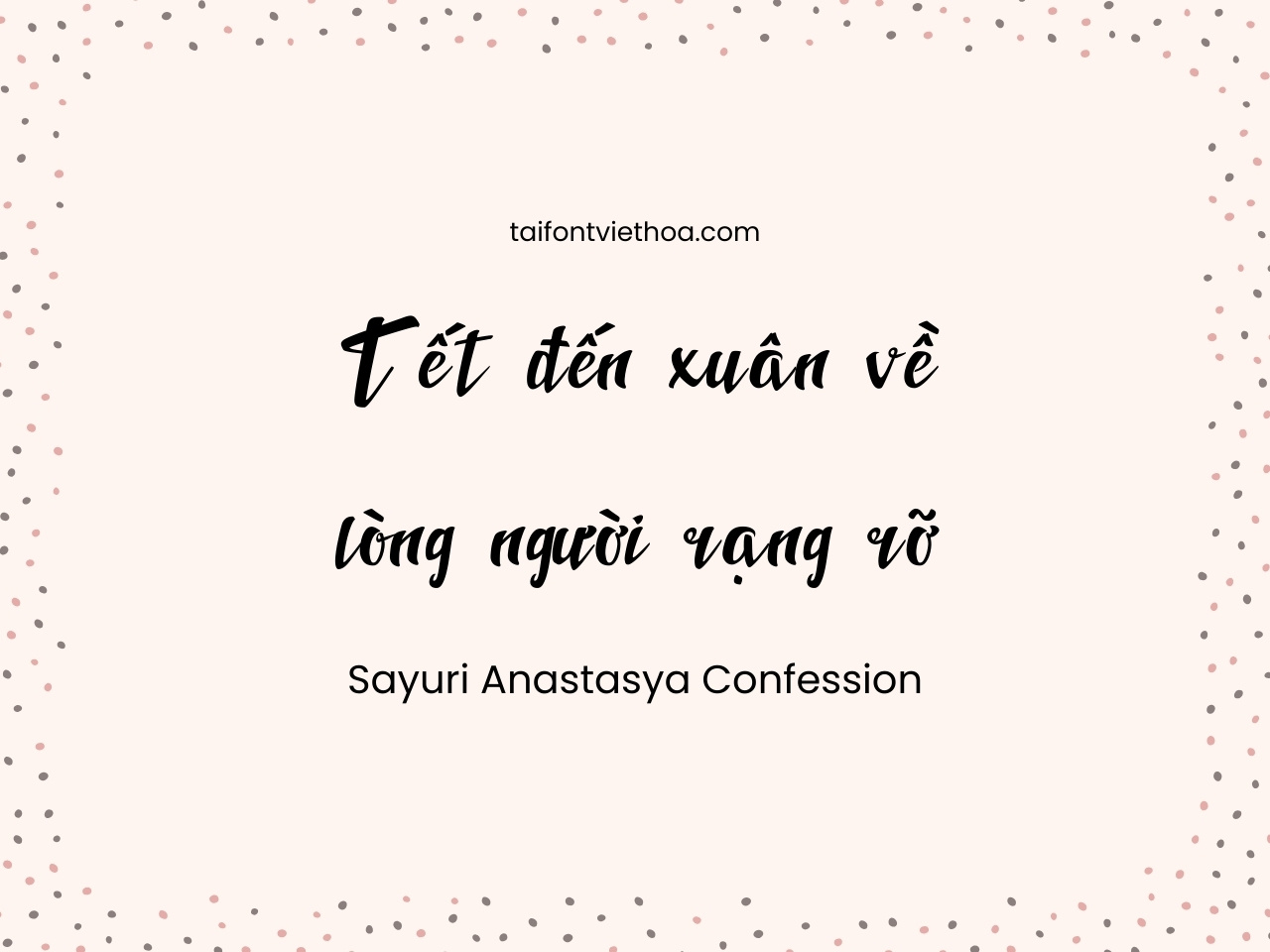
Font việt hóa Sayuri Anastasya Confession
Giới thiệu về font Sayuri Anastasya Confession
Sayuri Anastasya Confession là một font chữ script mang phong cách lãng mạn và đầy cảm xúc, thường được sử dụng trong các thiết kế nữ tính, thiệp cưới và branding nhẹ nhàng. Font được Việt hóa bởi Sayuri, hỗ trợ đầy đủ tiếng Việt với hệ dấu mềm mại, rõ ràng và sắc nét. Ngoài tiếng Việt, font còn tương thích với hơn 40 ngôn ngữ nhờ tích hợp bảng mã Latin và Latin Extended, giúp nhà thiết kế dễ dàng triển khai các dự án đa quốc gia. Font đã được taifontviethoa.com chọn lọc và kiểm duyệt chất lượng thực tế, sẵn sàng phục vụ cộng đồng sáng tạo Việt Nam trong nhiều ứng dụng thiết kế mang tính cảm xúc và thẩm mỹ cao.
Đặc điểm thiết kế và ứng dụng của Sayuri Anastasya Confession
Font mang đậm nét thư pháp nghệ thuật với các đường uốn lượn bay bổng, độ dày trung bình, tạo nên sự mềm mại, nữ tính nhưng vẫn giữ được sự rõ ràng khi hiển thị. Ligatures được chăm chút kỹ lưỡng giúp các ký tự liền mạch và mang cảm giác viết tay chân thực. Đây là lựa chọn lý tưởng cho các thiết kế yêu cầu sự duyên dáng và tinh tế.
Sayuri Anastasya Confession phù hợp cho các thiết kế thiệp cưới, thiệp mời, logo cá nhân, blog thời trang, bao bì mỹ phẩm hoặc bất kỳ dự án nào muốn truyền tải sự ngọt ngào và cảm xúc. Các ngành nghề phù hợp gồm: tổ chức sự kiện, wedding planner, thời trang nữ, mỹ phẩm, spa và sáng tạo nội dung hướng đến phụ nữ.